【繁而美的距離】早前在時代廣場舉辦的文字設計展覽《繁而美的距離》,當中的展品皆出自填詞人林若寧和最近榮獲DFA Awards DESIGN FOR ASIA AWARDS 2021 – Merit Award 的字體設計師威洪。
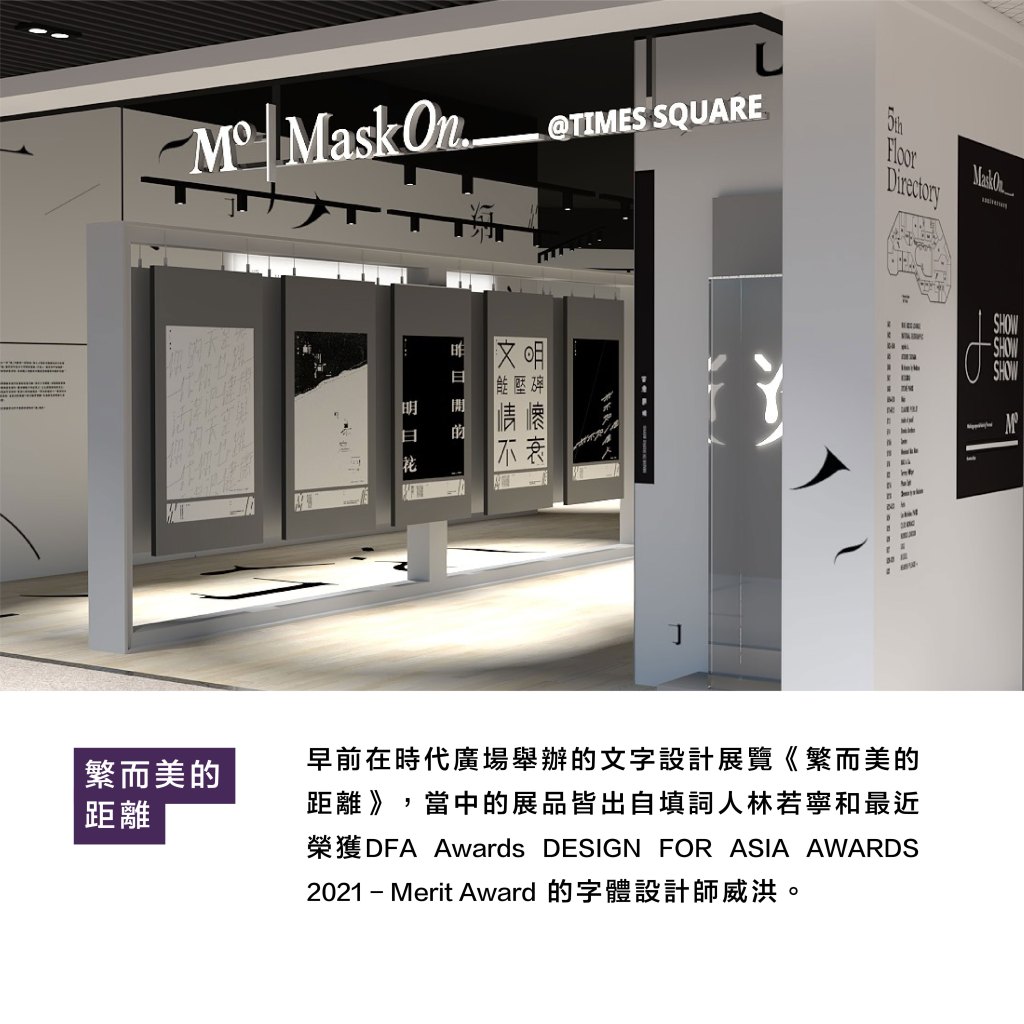
是次展覽以「距離」為題,由本地口罩品牌MaskOn為慶祝品牌成立一週年而策劃。由林若寧精心挑選10首關於距離的廣東歌詞,再由威洪以字體設計演繹出其對歌詞的感受。
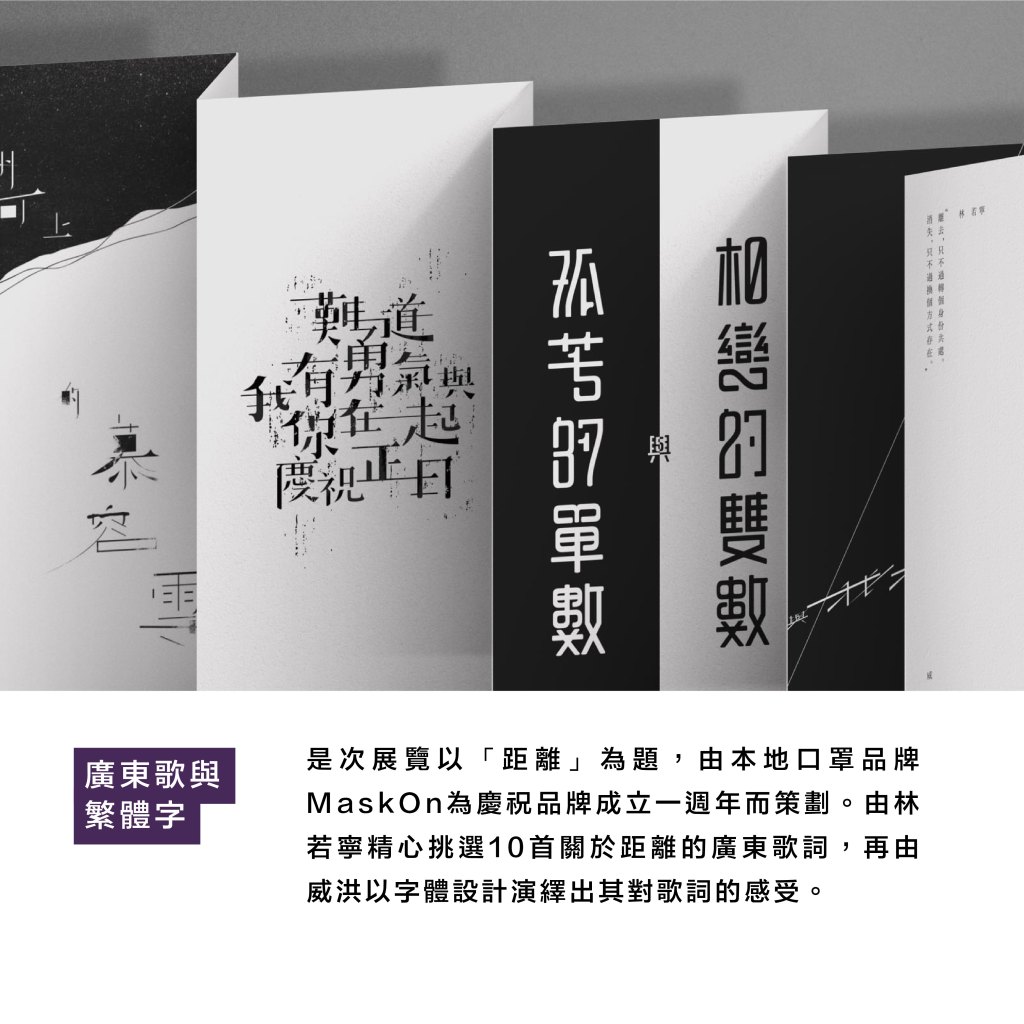
除了字體設計和排版,作品設計更揉合了黑白與光影的交錯,展現出不同質感的距離。其中場內的一個螢幕更透過投影和體感互動技術,投射出可讓觀眾觸碰互動的歌詞文字,從而衍生出另一種感覺的距離。
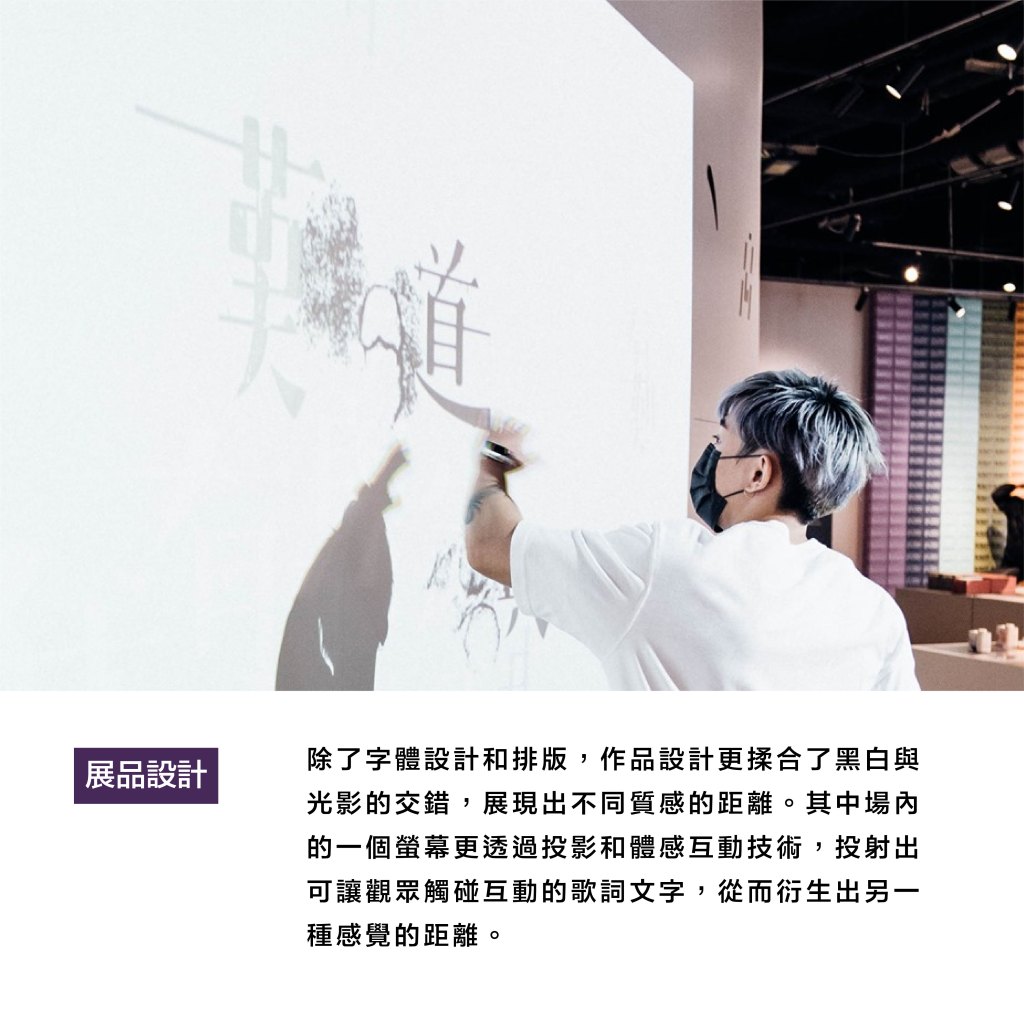
隨展覽推出的限量歌詞口罩收納套設計亦別出心裁,在透明的兩面膠片上分別印上不同筆劃,只有收納套的這兩面貼合在一起時才能重疊出一句完整的歌詞,正好反映了近年大家被疫情無奈地阻隔出的距離。